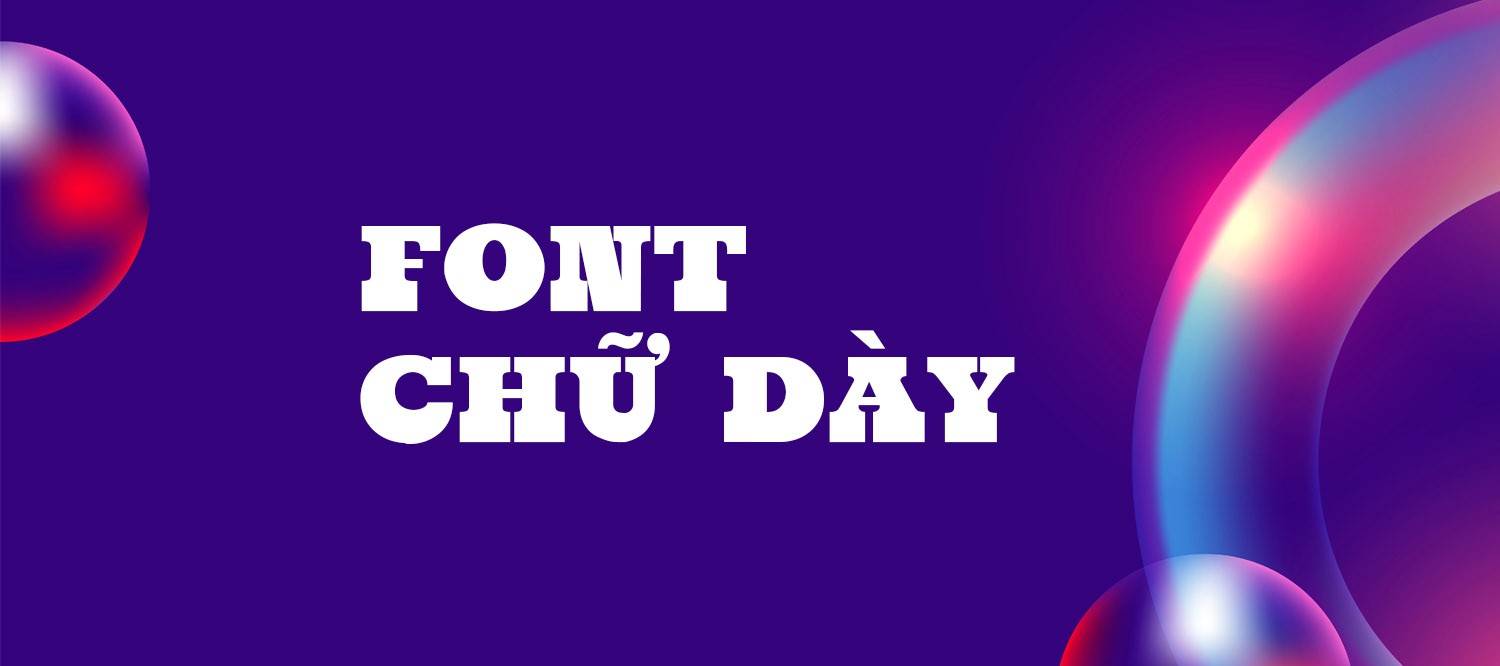
![[Tải xuống] Danh Sách 17+ Kiểu Font Chữ Dày, Đậm Việt Hoá Cho Thiết Kế](https://cdn.s99.vn/blog/s99.vn-font-chu-day-viet-hoa-1500-x-666.jpg)
Font chữ dày không chỉ là một yếu tố thị giác mà còn là công cụ truyền tải cảm xúc và bản sắc thương hiệu một cách mạnh mẽ. Với độ dày nét nổi bật, các kiểu chữ này thường được sử dụng để tạo tiêu đề thu hút, tăng tính nhận diện và tạo điểm nhấn trong mọi thiết kế từ poster quảng cáo đến giao diện website, bao bì sản phẩm hay ấn phẩm truyền thông.
Trong thời đại thiết kế lấy người dùng làm trung tâm, font chữ dày càng đóng vai trò quan trọng bởi khả năng đảm bảo độ dễ đọc, tạo ấn tượng mạnh và tăng độ tương phản – đặc biệt khi kết hợp cùng các nền màu sắc mạnh mẽ. Từ các thương hiệu quốc tế đến các thiết kế cá nhân, xu hướng sử dụng font chữ đậm, dày đang ngày càng phổ biến hơn bao giờ hết.
Bài viết này sẽ giới thiệu đến bạn 17 kiểu font chữ dày đã được Việt hóa, được chọn lọc kỹ càng theo từng phong cách và mục đích sử dụng, kèm hướng dẫn tải về, ứng dụng thực tế, xu hướng năm 2025 và những mẹo hữu ích để khai thác tối đa sức mạnh thị giác của chúng.
Danh sách dưới đây tập hợp 17 font chữ dày đẹp, đậm chất cá tính, đã được Việt hóa đầy đủ dấu tiếng Việt, phù hợp cho nhiều mục đích thiết kế khác nhau từ tiêu đề, poster đến bao bì sản phẩm. Tất cả đều được chọn lọc theo tiêu chí: độ dày rõ nét, phong cách đa dạng, khả năng ứng dụng cao và đặc biệt là miễn phí tải về hoặc thuộc nguồn đáng tin cậy.
TH Cungcap 12 là một font chữ sans-serif mang phong cách cứng cáp, hiện đại với các nét in đậm, vuông vức và mạnh mẽ. Thiết kế góc cạnh của font rất phù hợp với các thiết kế cần thể hiện sức mạnh, sự chắc chắn như poster game, banner ngành cơ khí, quân sự hoặc tiêu đề công trình. Đây là lựa chọn tuyệt vời cho những dự án cần nhấn mạnh tính kỹ thuật và nam tính.
TH Round Eight gây ấn tượng với phong cách chữ dày, đậm, nhưng lại có các góc bo mềm mại giúp tổng thể trở nên thân thiện và hiện đại. Font rất phù hợp cho các thiết kế thể thao, banner quảng bá sự kiện vận động hoặc thương hiệu mang tính năng động. Sự kết hợp giữa cứng cáp và mềm mại trong từng chữ cái mang lại hiệu ứng thị giác rất cân đối.
Bungee Regular mang tinh thần vui nhộn, nổi bật và trẻ trung với các nét chữ to, đậm và đầy đặn. Phông chữ này rất lý tưởng để sử dụng trong các dự án sáng tạo như tiêu đề hoạt hình, thiết kế thương hiệu trẻ hoặc chiến dịch quảng cáo mang tính giải trí cao. Điểm cộng lớn là font có hỗ trợ tiếng Việt đầy đủ và trình bày rất tốt ở kích thước lớn.
SVN Gilroy là bộ font sans-serif hiện đại, được Việt hóa từ font nổi tiếng Gilroy. Font sở hữu nhiều trọng lượng từ Light đến ExtraBold, nhưng bản Bold và Heavy của nó đặc biệt lý tưởng cho thiết kế tiêu đề, ứng dụng UI/UX hoặc branding startup. Kiểu dáng hiện đại, tối giản và cực kỳ chuyên nghiệp giúp SVN Gilroy trở thành font "quốc dân" của thế hệ thiết kế mới.
TH Hoaico 1 là font chữ mang đậm tinh thần ngày Tết cổ truyền với kiểu dáng retro, gợi nhớ đến biển hiệu, bao bì, hoặc nhãn mác những năm 80–90. Các đường nét dày, bo nhẹ tạo cảm giác thân thuộc và truyền thống, rất thích hợp cho thiết kế bao lì xì, poster Tết, hoặc các ấn phẩm truyền thông dịp lễ hội.
Font TH Cungcap 7 nổi bật với độ dày cực khủng và phong cách thiết kế như một "khối sắt di động". Kiểu chữ này thể hiện được cảm giác sức mạnh, cơ bắp và chiến đấu, nên thường được sử dụng trong poster game hành động, quân đội, hoặc thiết kế ngành cơ khí nặng. Đây là lựa chọn không thể thiếu nếu bạn muốn gây ấn tượng ngay từ cái nhìn đầu tiên.
TH Cartoon 4 là font hoạt hình mang tính biểu cảm cao với các đường nét cong tròn, đáng yêu và đầy năng lượng. Rất thích hợp cho các sản phẩm hướng đến trẻ em như sách vải, bao bì kẹo, sữa, hoặc poster phim hoạt hình. Kiểu chữ này có thể "truyền cảm hứng" chỉ bằng chính hình dáng của nó.
TH Wosker là font thể thao sắc sảo với nét chữ in đậm, hơi nghiêng, mang lại cảm giác tốc độ và chuyển động. Đây là font tuyệt vời để ứng dụng trên áo đấu, poster giải thể thao, hay logo các đội tuyển. Nó truyền tải được tinh thần cạnh tranh, bứt phá và sức mạnh cơ bắp – rất phù hợp cho những thiết kế cần sự quyết liệt.
TH Chrone là font in đậm với phong cách hiện đại, mạnh mẽ, góc cạnh nhưng vẫn đảm bảo dễ đọc. Được thiết kế tối ưu cho tiêu đề và in ấn, font phù hợp cho các poster quảng bá, băng rôn sự kiện hoặc thiết kế cần tạo sự chú ý nhanh chóng. Kiểu dáng gọn gàng, rõ ràng giúp TH Chrone trở nên linh hoạt trong nhiều lĩnh vực.
TH Striger mang hơi hướng quân đội, thể thao điện tử với cấu trúc vững chãi và các cạnh mạnh mẽ. Là lựa chọn hàng đầu cho các thiết kế liên quan đến game, eSport, thể thao chuyên nghiệp, font này truyền tải rất tốt tinh thần chiến đấu và sự máu lửa trong từng chữ cái.
Gây chú ý mạnh mẽ
Tăng nhận diện thương hiệu
Đọc nhanh, quét dễ
Thể hiện cá tính thiết kế
Tạo cảm giác chuyên nghiệp
Khi bạn cần sự tối giản, tinh tế
Với văn bản dài, tài liệu cần độ dễ đọc cao
Trên nền ảnh phức tạp, font dễ bị chìm
Hãy chọn font chữ dày như chọn giọng nói trong thiết kế: mạnh mẽ, rõ ràng nhưng đúng lúc và tiết chế. Việc kết hợp linh hoạt giữa font dày và font phụ trợ sẽ giúp bạn xây dựng một thiết kế thuyết phục cả về thẩm mỹ lẫn thông điệp.